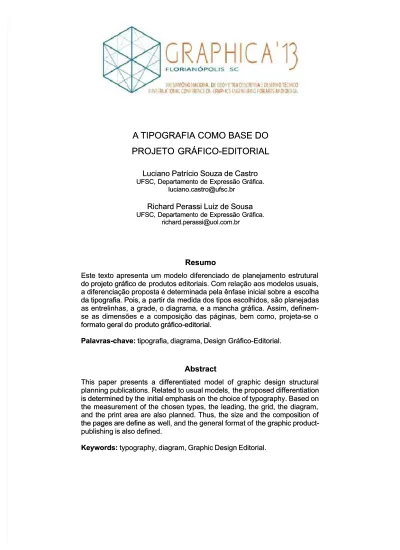
A TIPOGRAFIA COMO BASE DO
TIPOGRAFIA COMO BASE DO
PROJETO GRÁFICO-EDITORIAL
Resumo Resumo
Este texto apresenta um modelo diferenciado de planejamento estrutural Este texto apresenta um modelo diferenciado de planejamento estrutural do projeto gráfico de
do projeto gráfico de produtos editoriais. Com relação aos modelos usuais, a diferenciação proposta é determinada pela ênfase inicial sobre a
a diferenciação proposta é determinada pela ênfase inicial sobre a escolhaescolha da tipografia. Pois, a
da tipografia. Pois, a partir da medida dos tipos escolhidos, são planejadas as entrelinhas, a grade, o diagrama, e a mancha gráfica. Assim, as entrelinhas, a grade, o diagrama, e a mancha gráfica. Assim, definem-se as dimensões e a composição das páginas, bem como, projeta-definem-se o se as dimensões e a composição das páginas, bem como, projeta-se o formato geral do
formato geral do produto gráfico-editorial.
Abstract Abstract
This paper presents a differentiated model of graphic design structural This paper presents a differentiated model of graphic design structural planning publications. Related to usual models,
planning publications. Related to usual models, the proposed differentiation is determined by the
is determined by the initial emphasis on s on the choice of typography. Based on the measurement of the chosen types, the leading, the grid, the diagram, the measurement of the chosen types, the leading, the grid, the diagram, and the print area are also planned. Thus, the size and the composition of and the print area are also planned. Thus, the size and the composition of the pages are define as
the pages are define as well, and the general format of the graphic product-publishing is also defined.
publishing is also defined.
1 Introdução
O incremento tecnológico na área editorial tornou-se mais relevante a partir da produção e do uso de tipos móveis pelo gráfico alemão Johannes Gutenberg (1398-1468). Primeiramente, esses tipos foram feitos de madeira e, logo em seguida, foram fundidos em metal. A tipografia fundada por Gutenberg retirou o processo gráfico-editorial da restrita escala da arte, inaugurando o domínio do planejamento tecnológico e superando o trabalho escultórico que, até então, dependia do entalhe de palavras e textos completos em uma única matriz de madeira.
A partição física das palavras em tipos de metal, além da já característica separação entre palavras e frases, impôs a percepção e a consideração antecipada das linhas verticais no planejamento da página impressa. Assim, além do paralelismo das linhas horizontais que, desde o início, serviram de orientação à linearidade do texto impresso, também, a organização e a demarcação das linhas verticais passou a ser considerada ação necessária ao planejamento da página impressa, no contexto do projeto gráfico-editorial.
Atualmente, Design Editorial é a expressão que representa a área de estudos e atividades gráficas, que é responsável pela criação e desenvolvimento dos projetos gráficos e pela supervisão tecnológica da produção gráfico-editorial (ADG, 2003). Devido à ênfase nos aspectos relacionados com a funcionalidade e a usabilidade nos produtos de Design, a ergonomia é percebida como solução central nos processos de projetação e produção. No produto gráfico-editorial, a grade, que também é denominada de grid , e o diagrama, que é definido sobre a grade, são os elementos
geométricos que organizam o processo de configuração ergonômica da diagramação. O uso da matemática e da geometria é responsável pela introdução do caráter lógico-científico no planejamento e no desenvolvimento dos produtos de Design. Assim, a ergonomia se caracteriza pela formulação lógico-racional de soluções estéticas, simbólicas e funcionais, com base na aplicação da matemática em geral e da geometria em particular, no processo de projetação e configuração dos produtos em geral e dos produtos gráfico-editoriais em particular.
O projeto e o produto gráfico-editorial devem primar pela: (1) ergonomia visual, que trata do planejamento estético; (2) ergonomia cognitiva, que trata do planejamento simbólico, visando garantir boas condições de leitura e interpretação da semântica gráfico-visual e do conteúdo verbal do produto editorial; (3) ergonomia funcional, que trata da acessibilidade e da usabilidade na interação entre os usuários e o produto gráfico-editorial. Entretanto, esses três parâmetros não são independentes entre si.